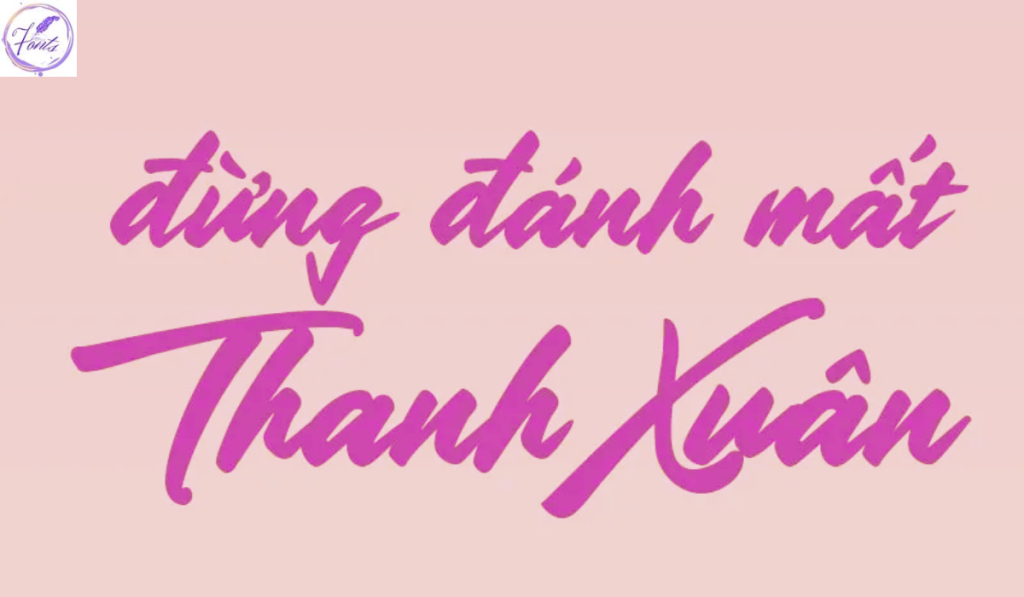
Font Constellation việt hóa
Tác giả: Chester Jenkins, Tracy Jenkins
Ngày phát hành: 1999
Ngôn ngữ: Đa ngôn ngữ
Bộ Font: Constellation
Phân loại: Cá tính, Độc đáo, Hiện đại
Kiểu chữ: Kiểu chữ viết tay (script)
Font constellation là một bộ font độc đáo và sáng tạo, được thiết kế để mang lại sự tinh tế và hiện đại cho các dự án thiết kế. Được phát triển bởi một nhóm các nhà thiết kế tài năng là Chester Jenkins, Tracy Jenkins vào năm 1999, font này nhanh chóng thu hút sự chú ý nhờ vào các đường nét sắc sảo và chi tiết tinh tế. Font constellation phù hợp cho nhiều loại hình thiết kế như logo, tiêu đề, và các sản phẩm truyền thông. Phiên bản Việt hóa của font constellation giúp người dùng Việt Nam dễ dàng sử dụng và sáng tạo trong các dự án của mình.
Đánh giá font constellation
Font constellation nhận được nhiều đánh giá tích cực từ cộng đồng thiết kế nhờ vào tính thẩm mỹ và tính linh hoạt của nó. Các nhà thiết kế đánh giá cao sự độc đáo và dễ đọc của font này, giúp truyền tải thông điệp một cách hiệu quả và ấn tượng. Font constellation không chỉ phù hợp cho các tiêu đề lớn mà còn đảm bảo tính dễ đọc cho các đoạn văn bản nhỏ. Phiên bản Việt hóa của font này cũng được đánh giá cao vì giữ nguyên được phong cách gốc, đồng thời bổ sung đầy đủ các ký tự tiếng Việt, đáp ứng mọi nhu cầu sử dụng.